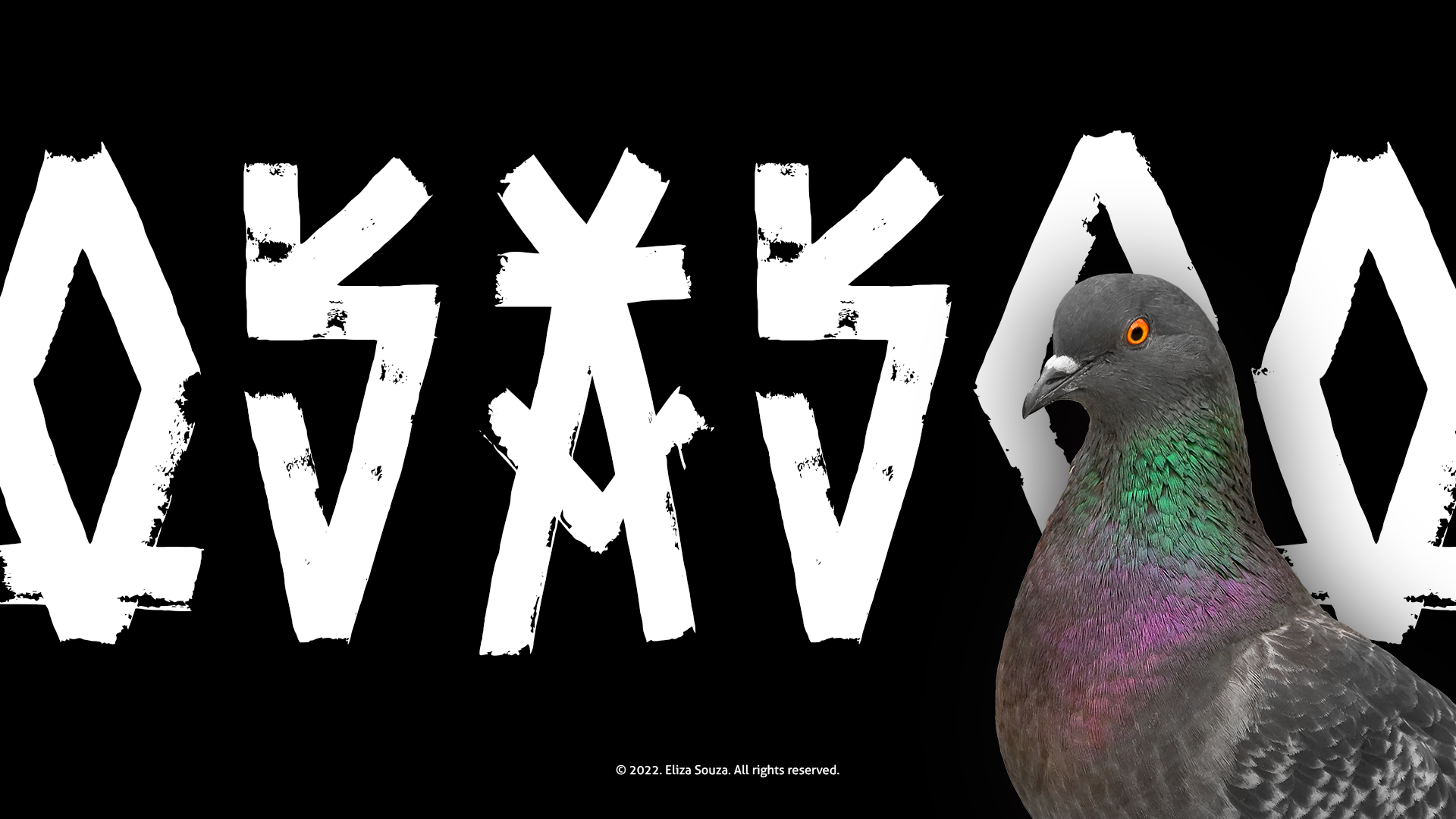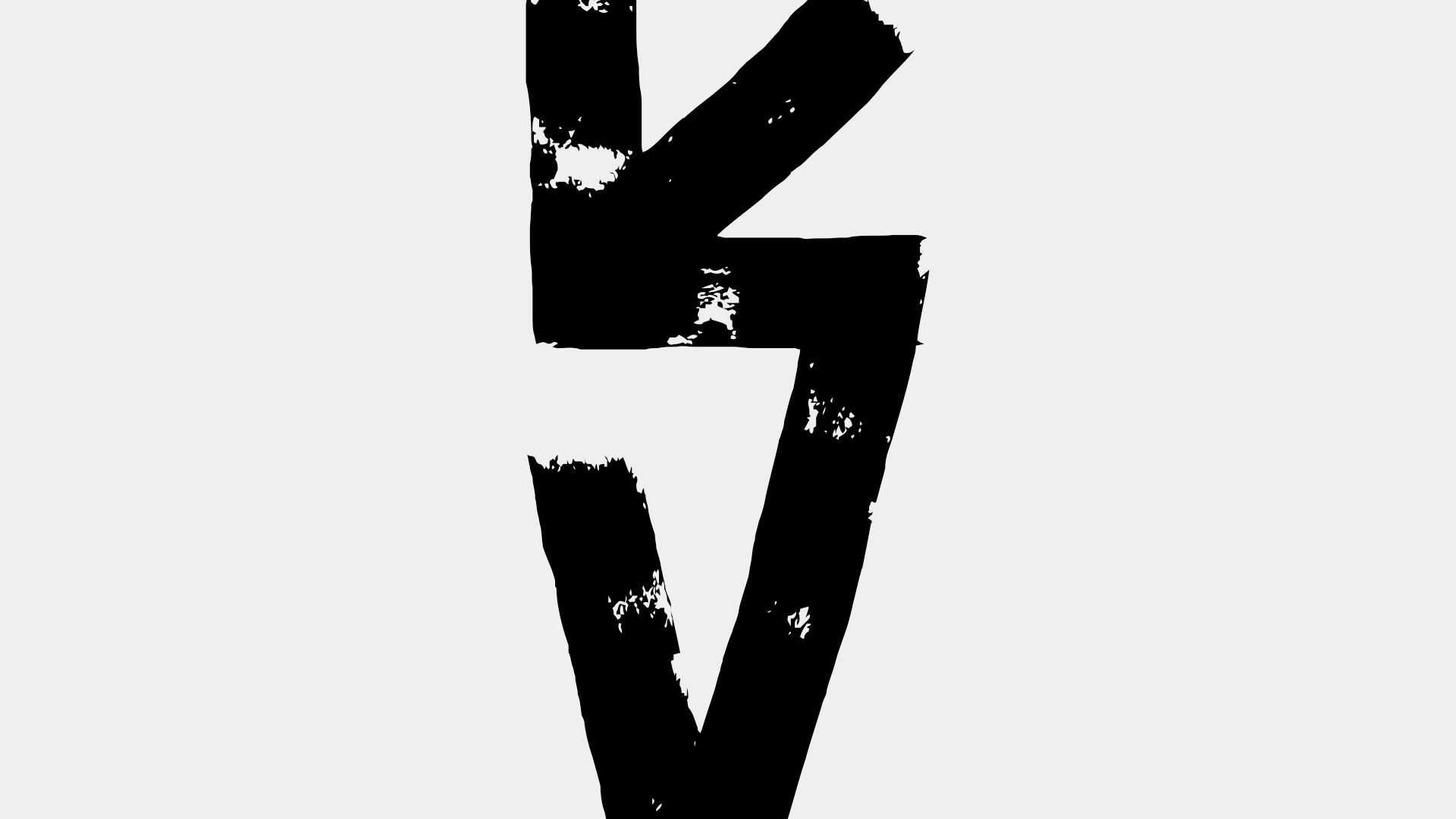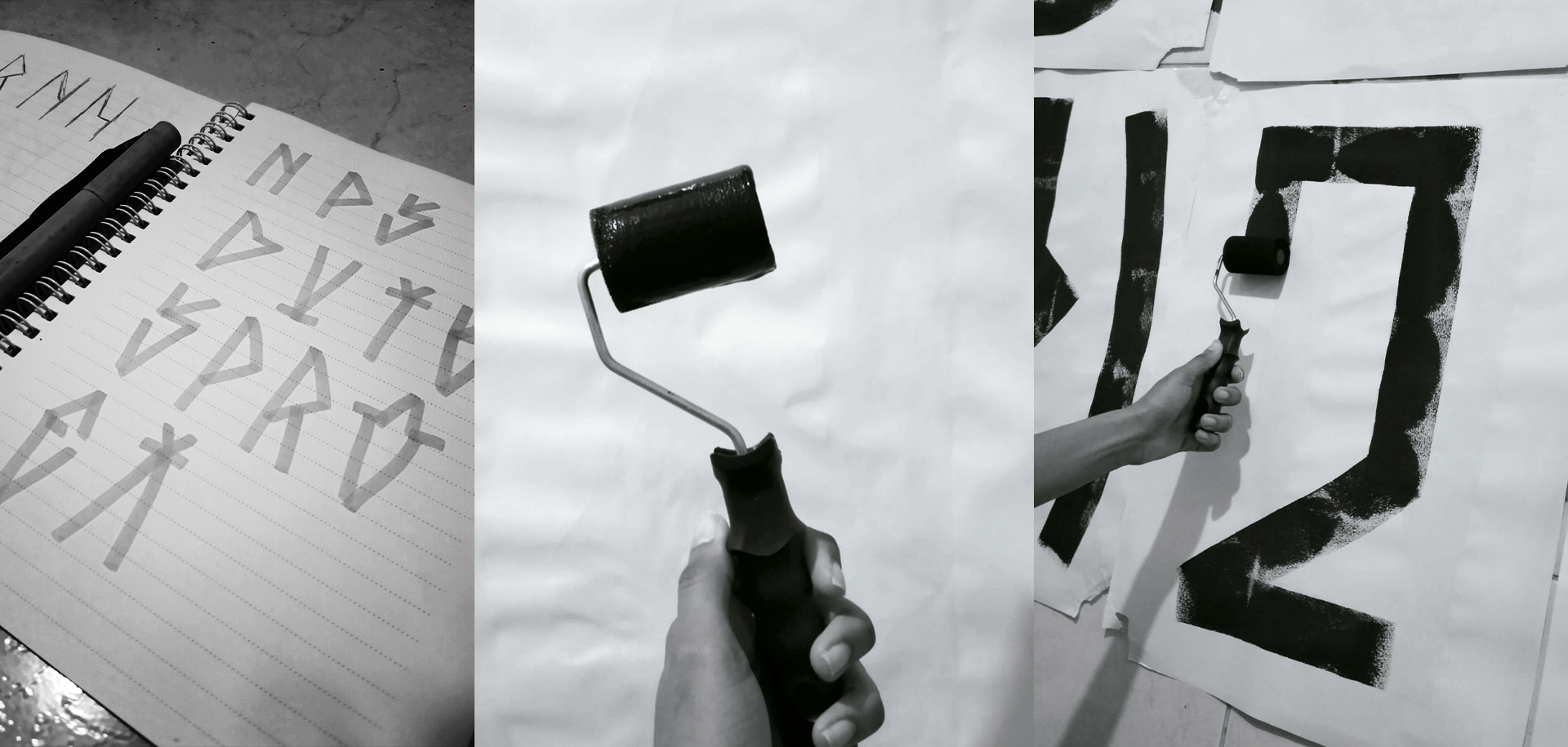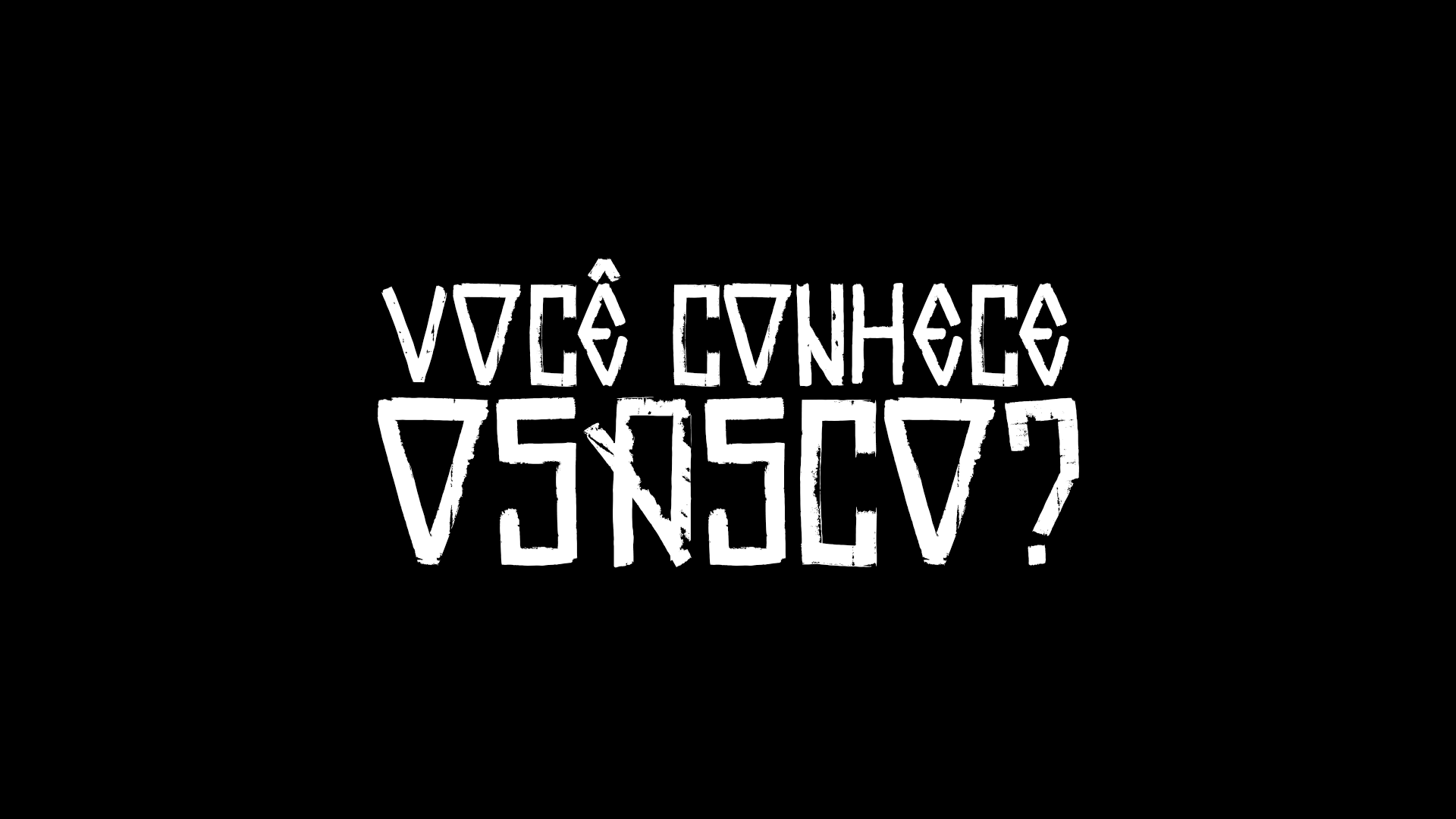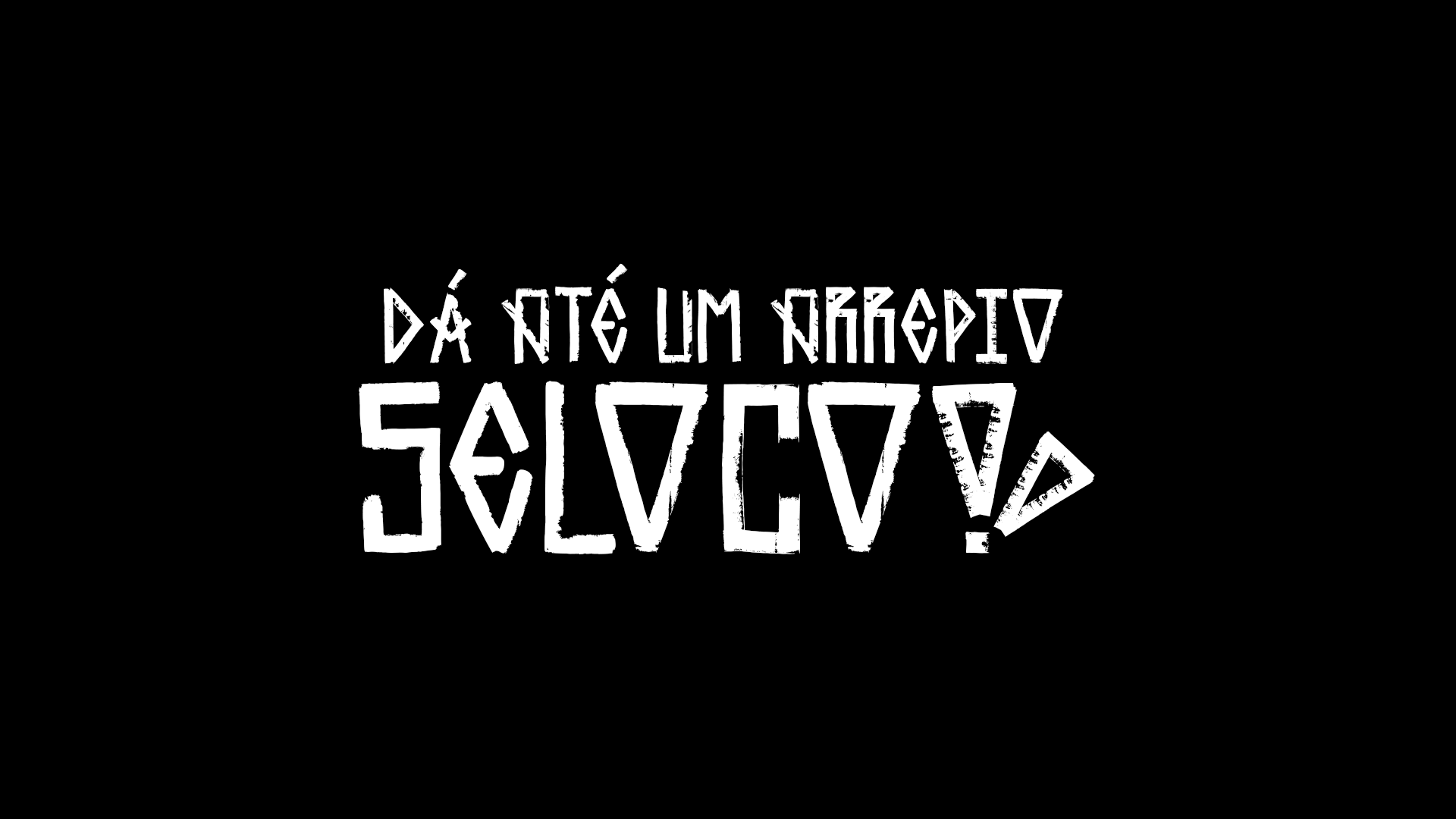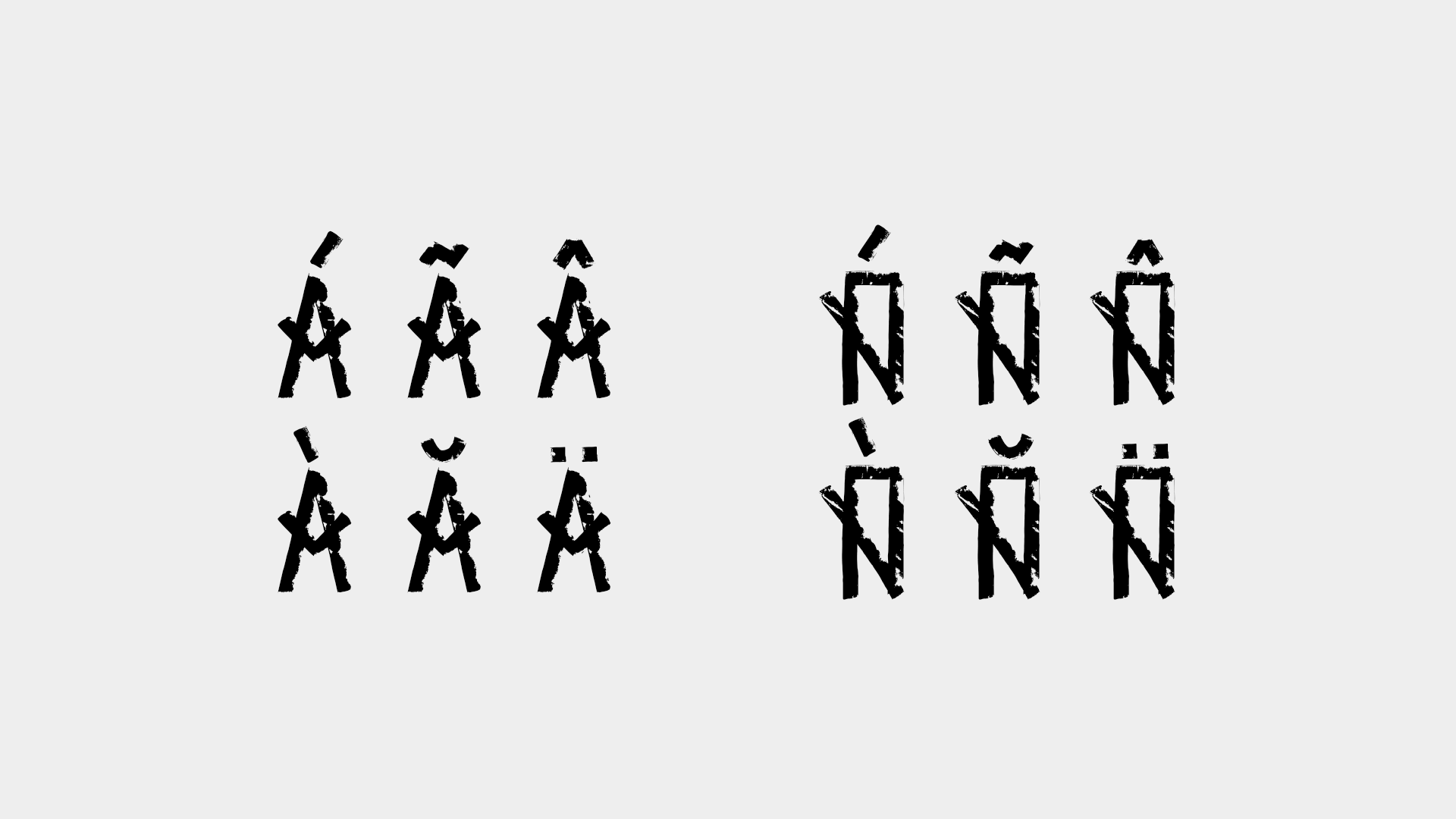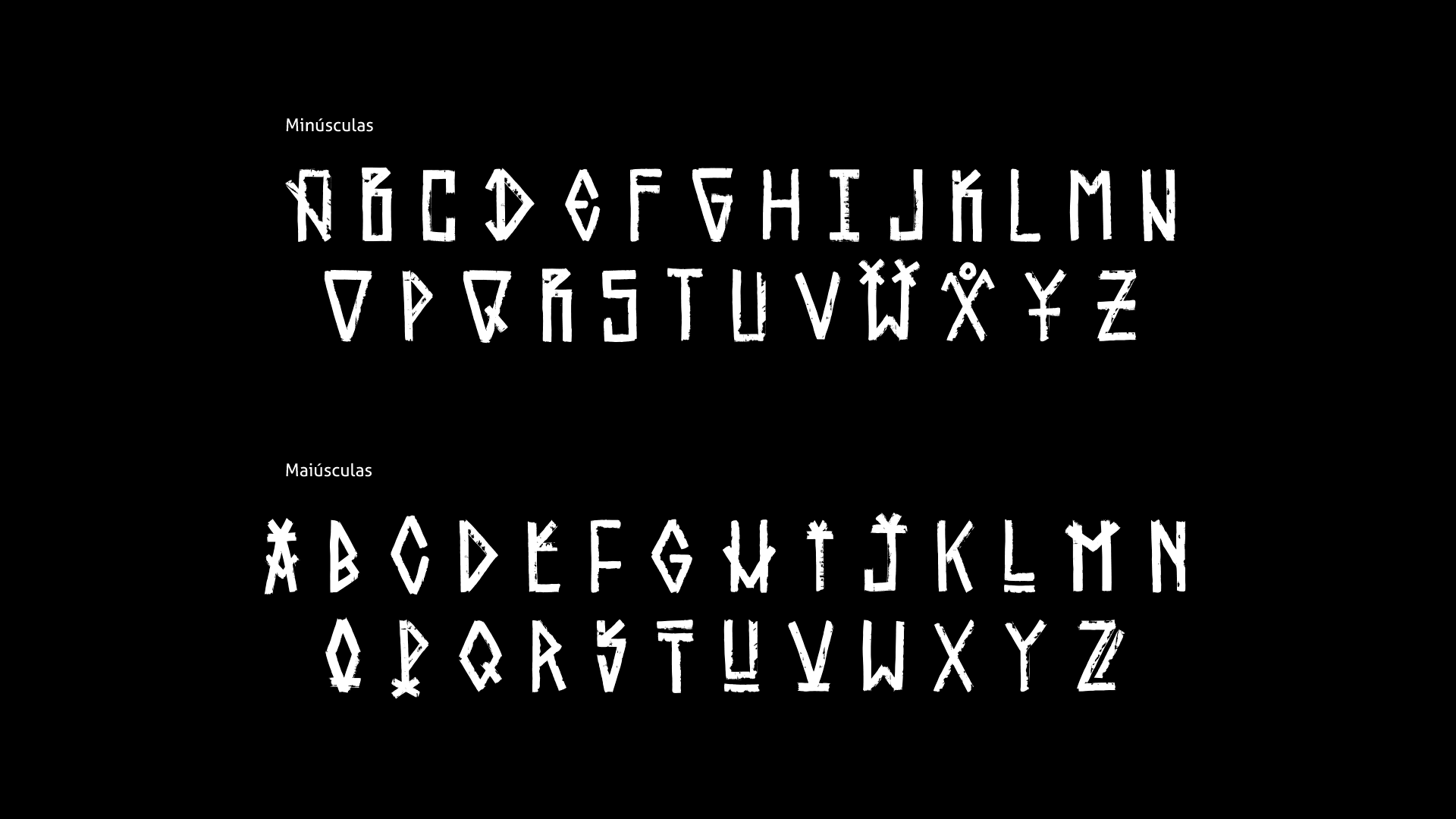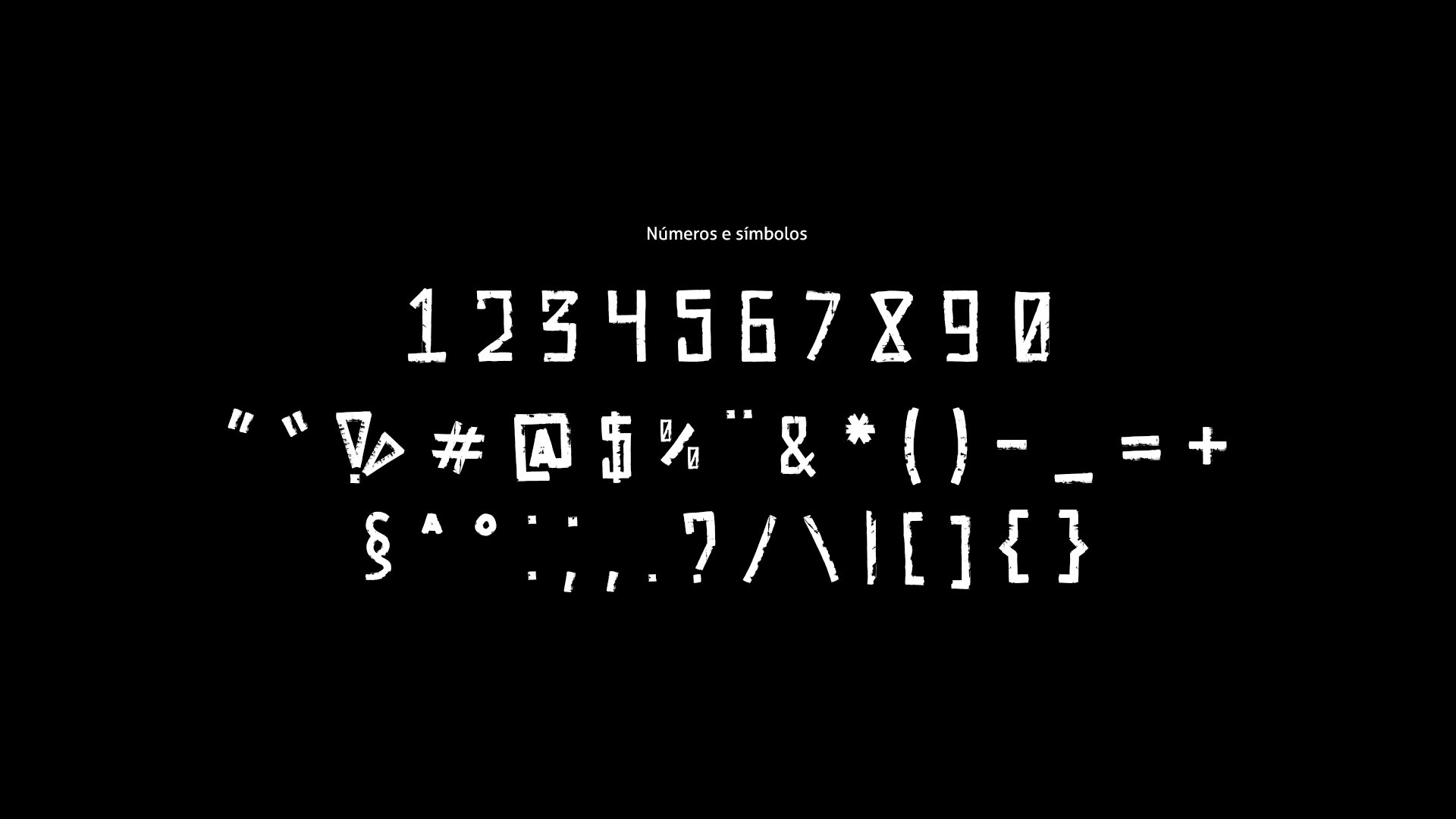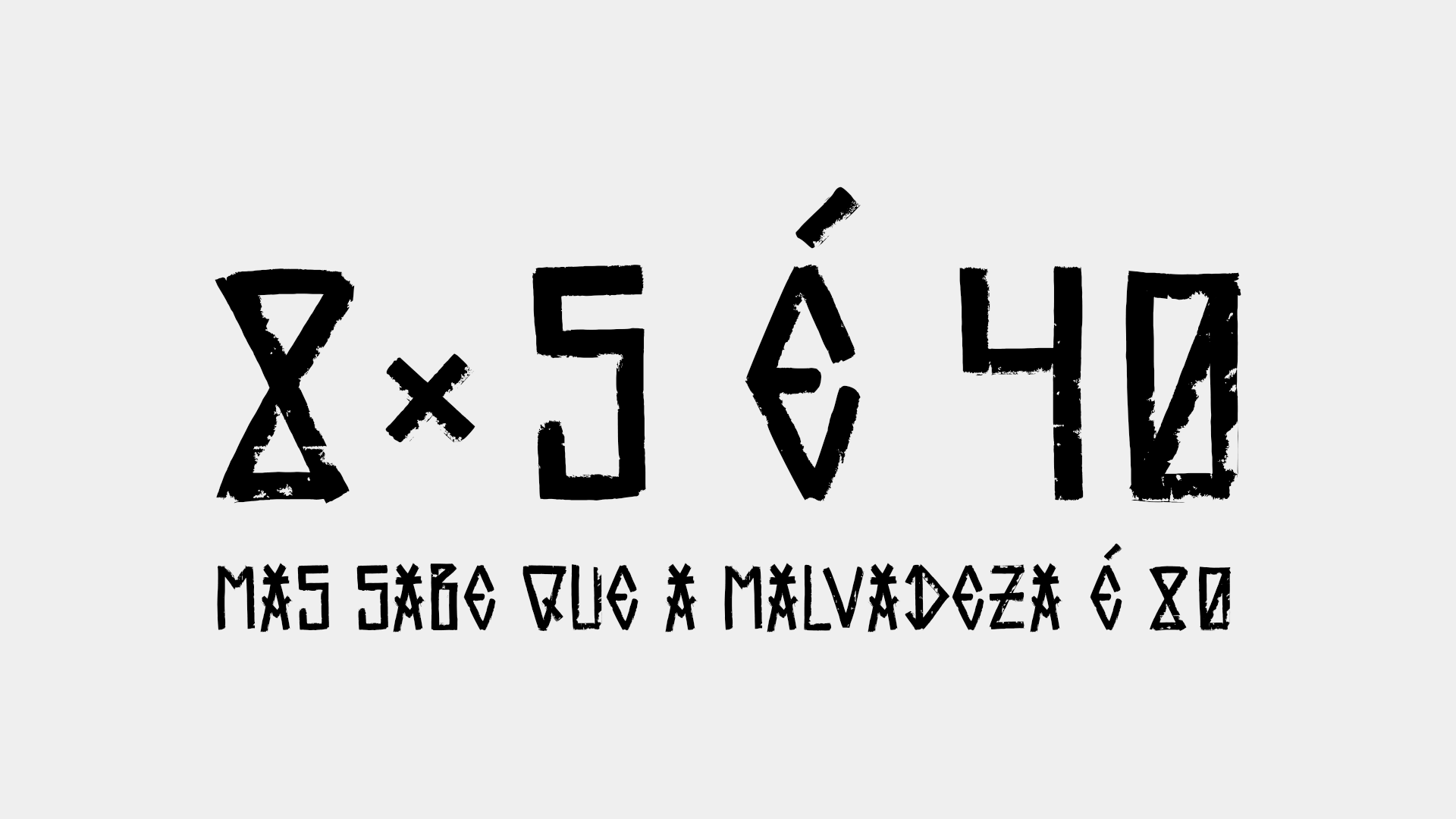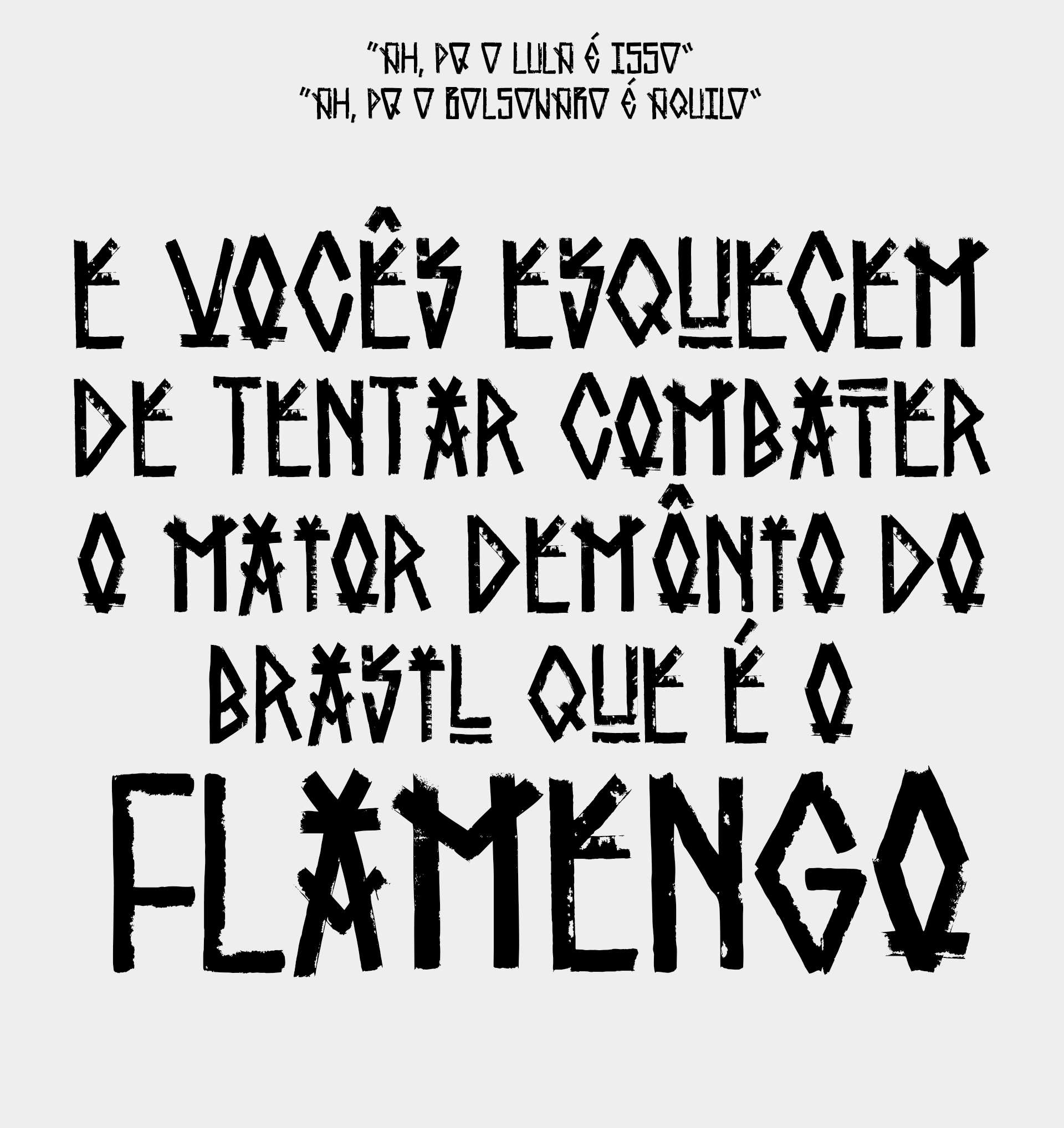
osasco type
“Osasco” é uma fonte display desenhada manualmente e ideal para títulos e textos grandes. Inspirada nas pixações da cidade de Osasco, localizada na região metropolitana de São Paulo, a fonte propõe resgatar as formas e os traçados de uma arte urbana que é vista como feia, suja e criminosa, mas que apesar disso, está presente na vida da população das cidades.
“Osasco” es una fuente display diseñada manualmente e ideal para títulos y textos grandes. Inspirada en las “pixações” de la ciudad de Osasco, localizada en la región metropolitana de São Paulo. La fuente propone rescatar las formas y los trazos de un arte urbana que es vista como fea, sucia y criminosa, pero que a pesar de eso, está presente en la vida de la población de las ciudades.
“Osasco” is a handheld typography and is ideal for titles and large text. Inspired by the graffiti in the city of Osasco, located in the metropolitan region of São Paulo, the typography proposes to rescue the forms and traces of urban art that are seen as ugly, dirty, and criminal, but which, despite this, is part of the people’s life.
type specimen
type designer eliza souza